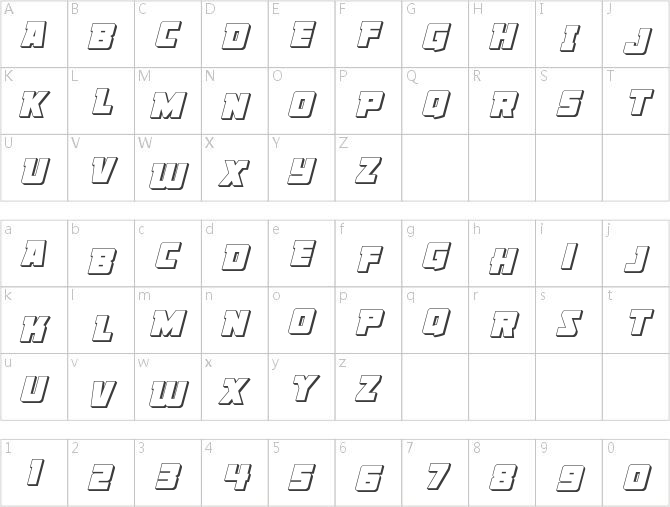
Liberty Legion 3D Italic
Liberty Legion 3D Italic介绍
Liberty Legion 3D Italic字体字库是一款让人赏心悦目、百看不厌的英文字体,适合各类广告和产品包装设计应用,字体大小0.04MB,格式为ttf字体,上传用户是Me / ,yD ,作者/版权方为未知